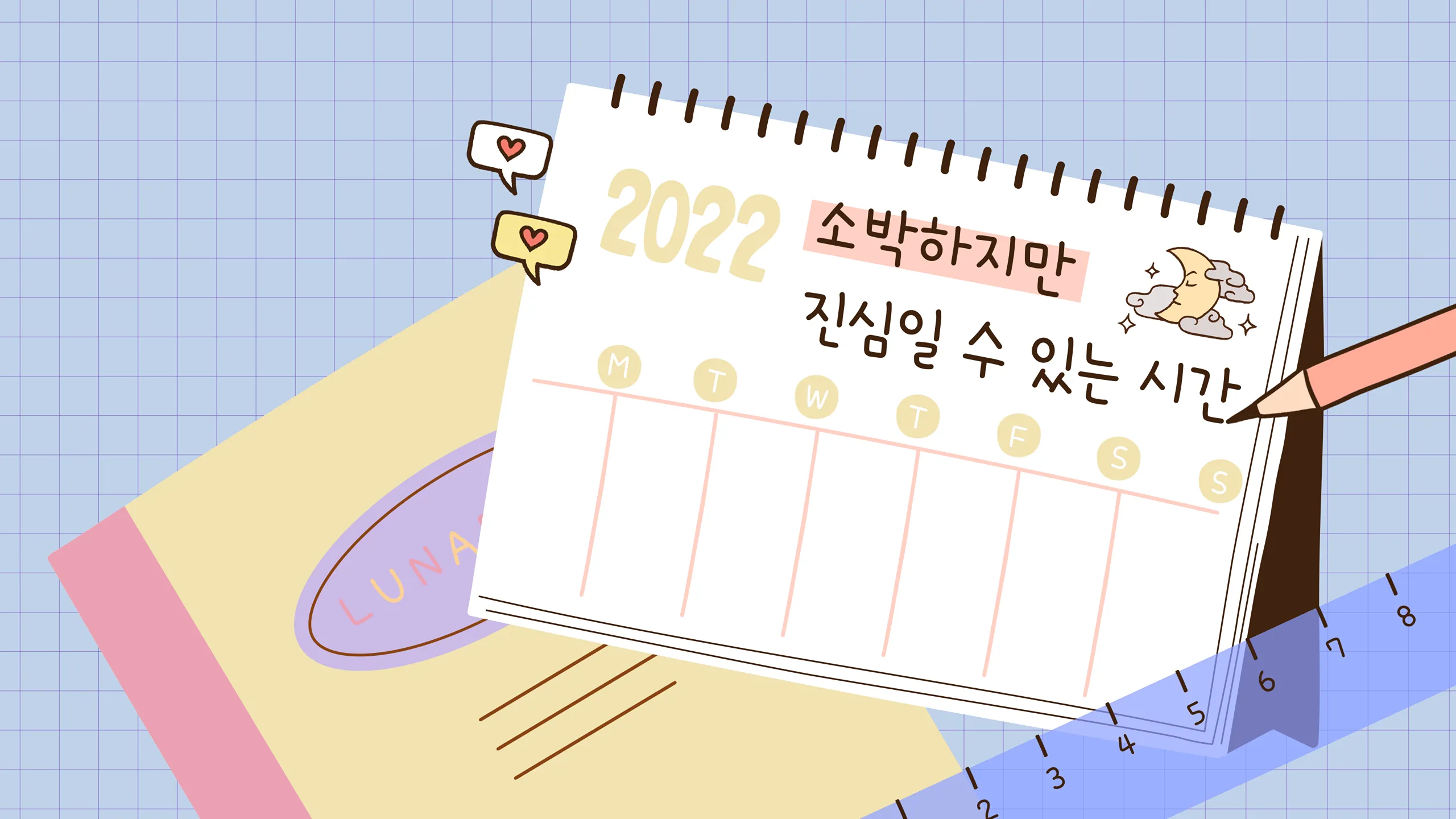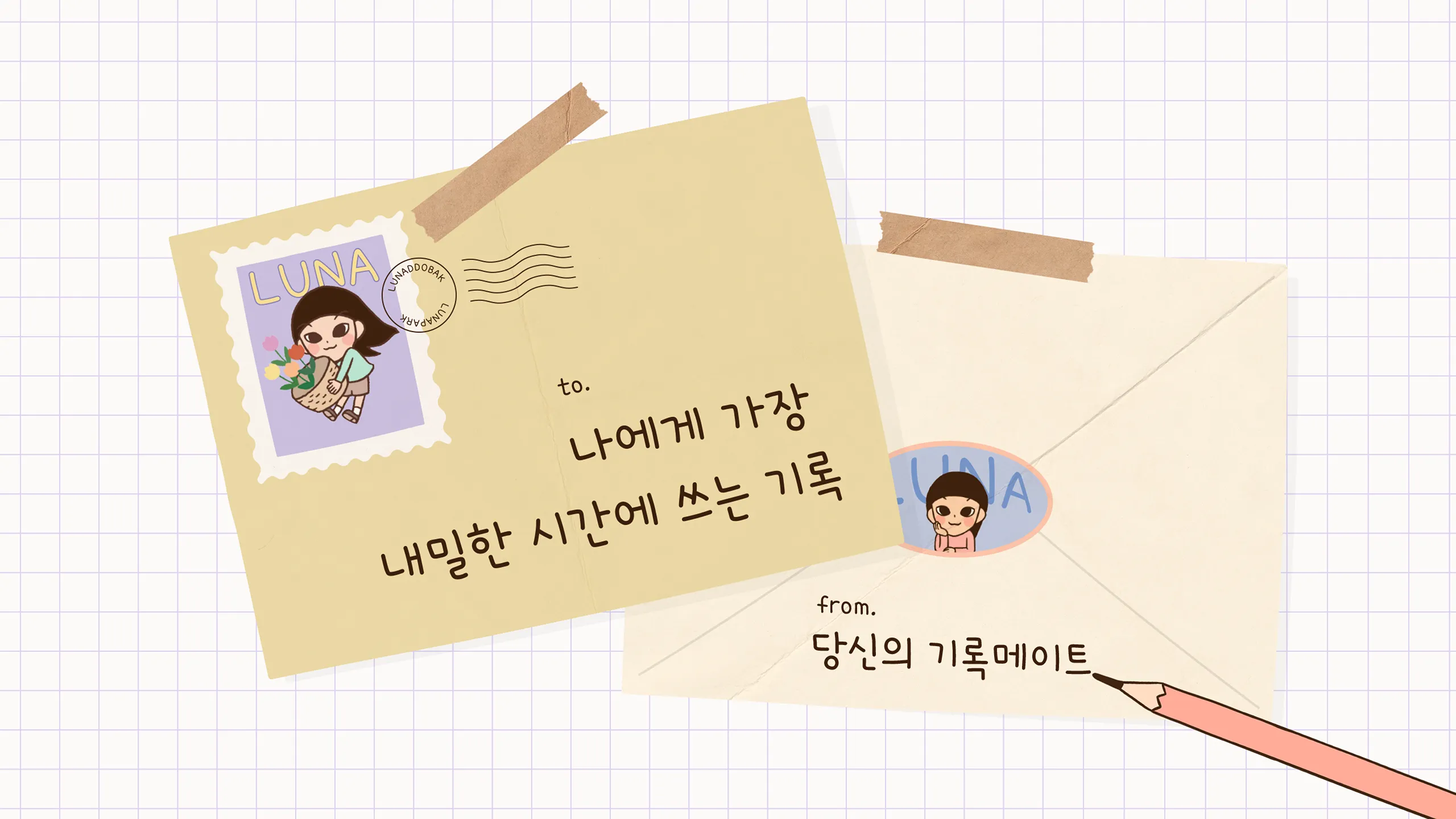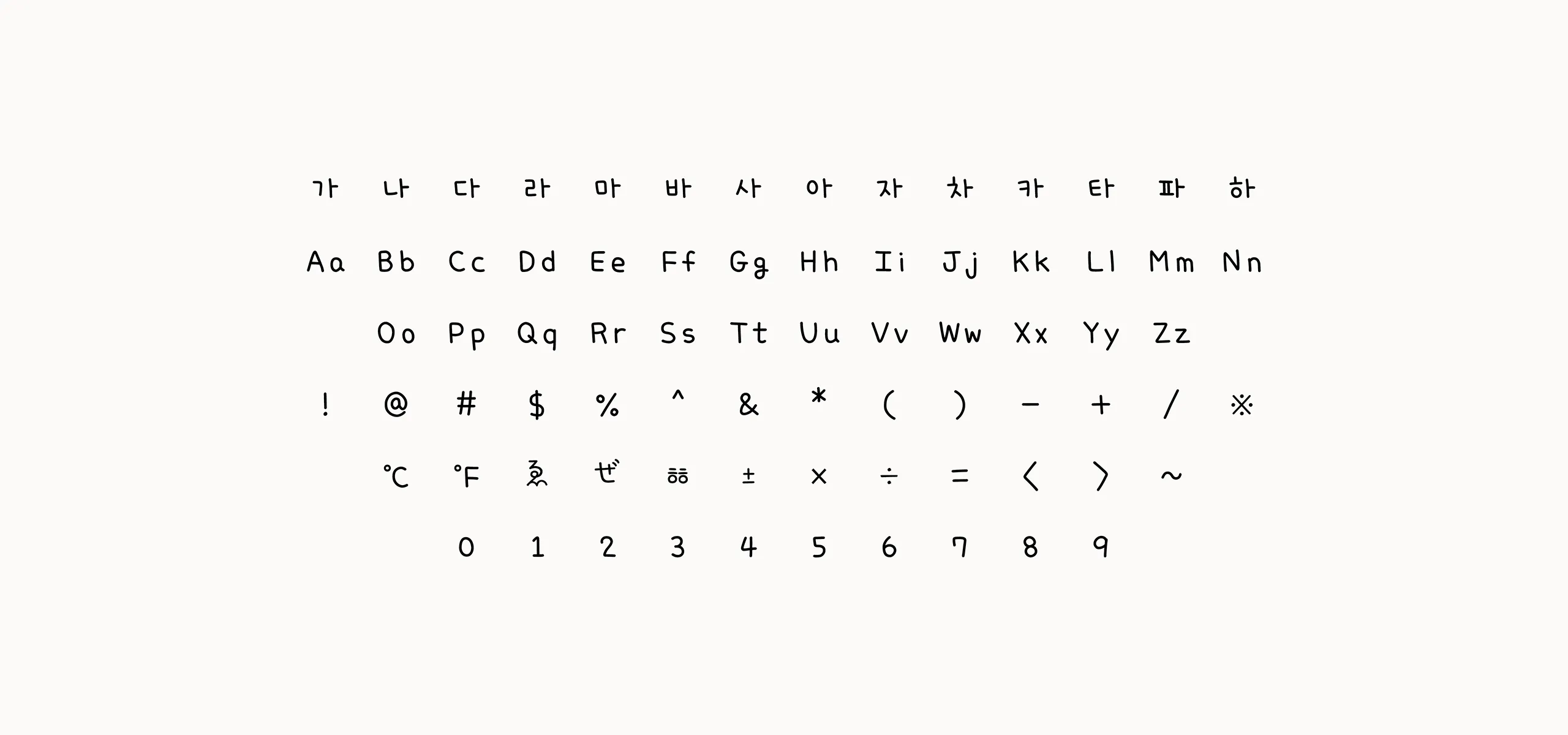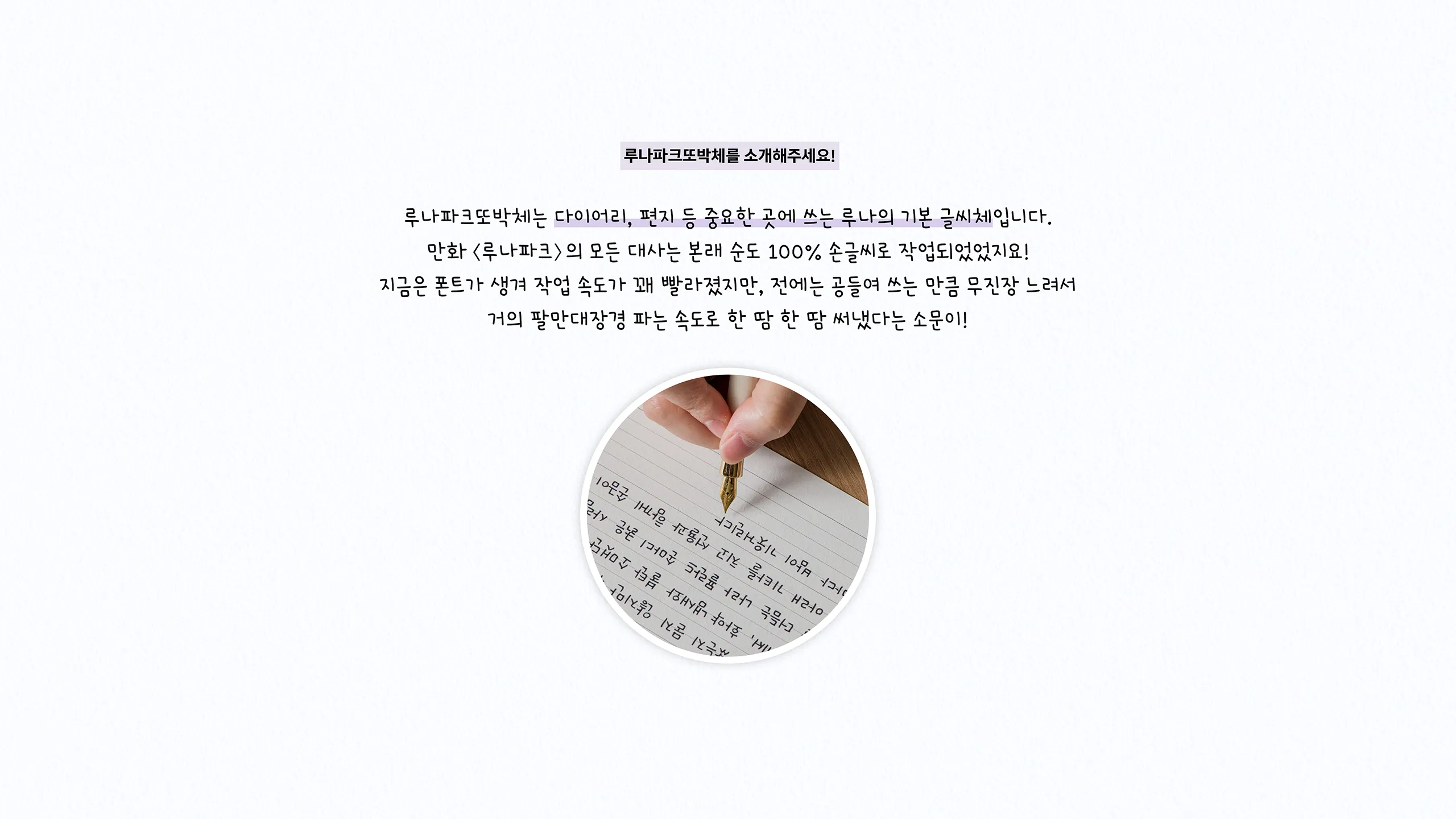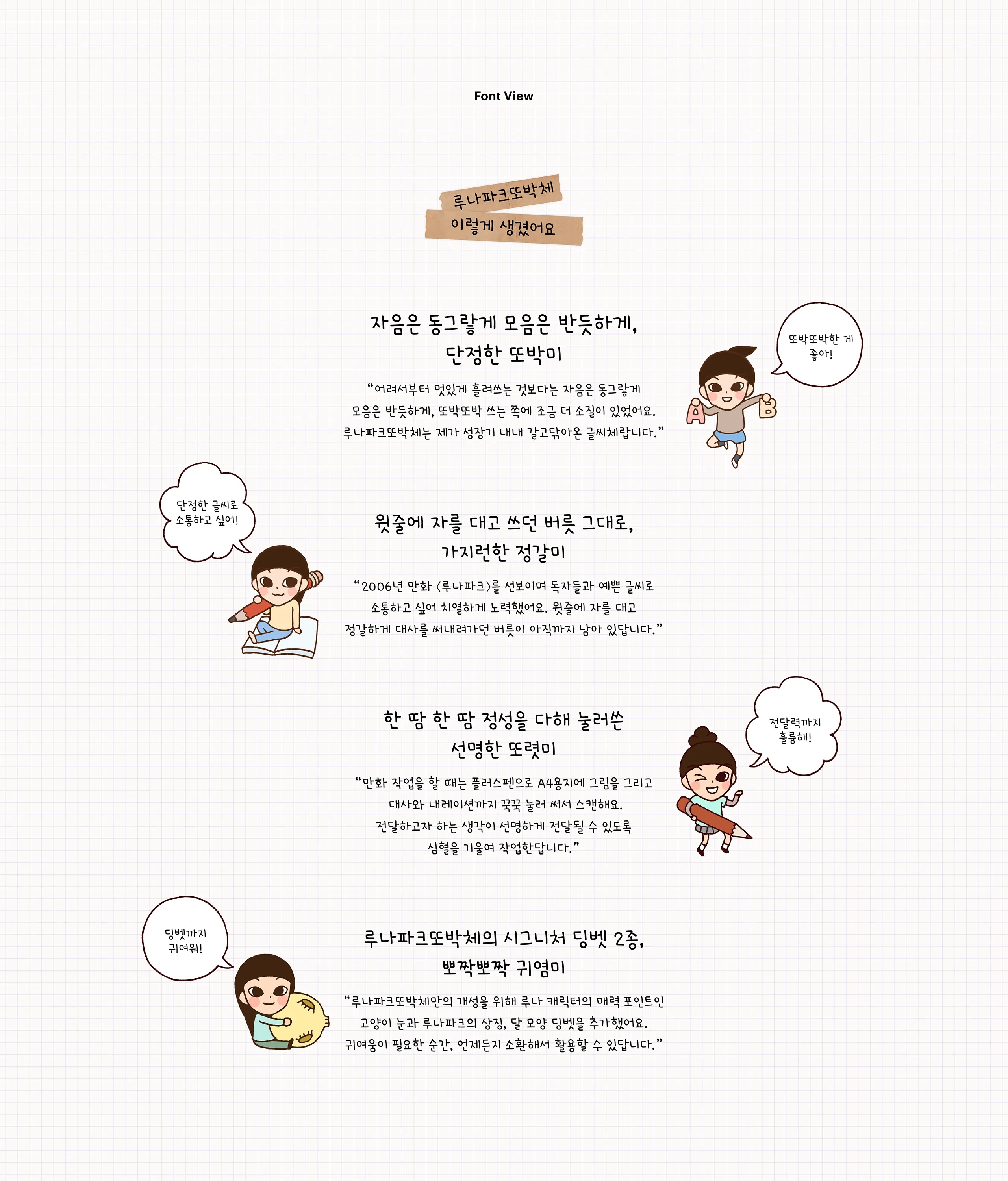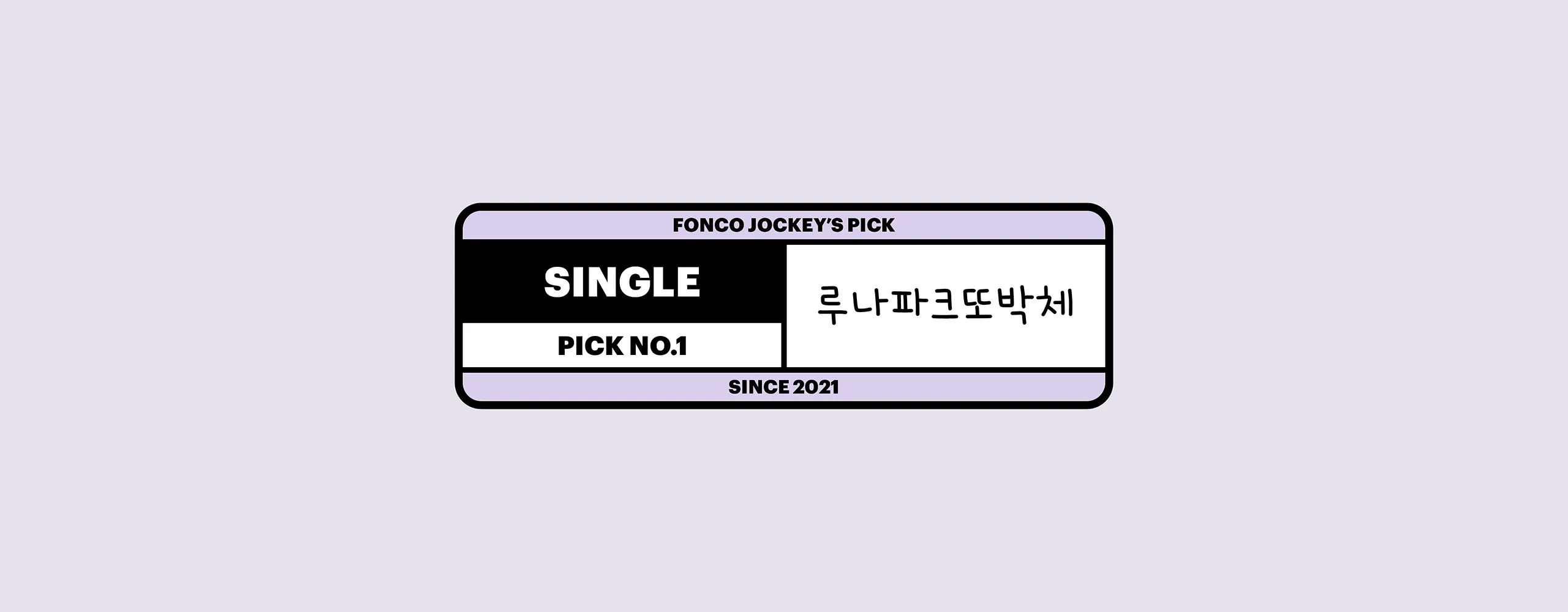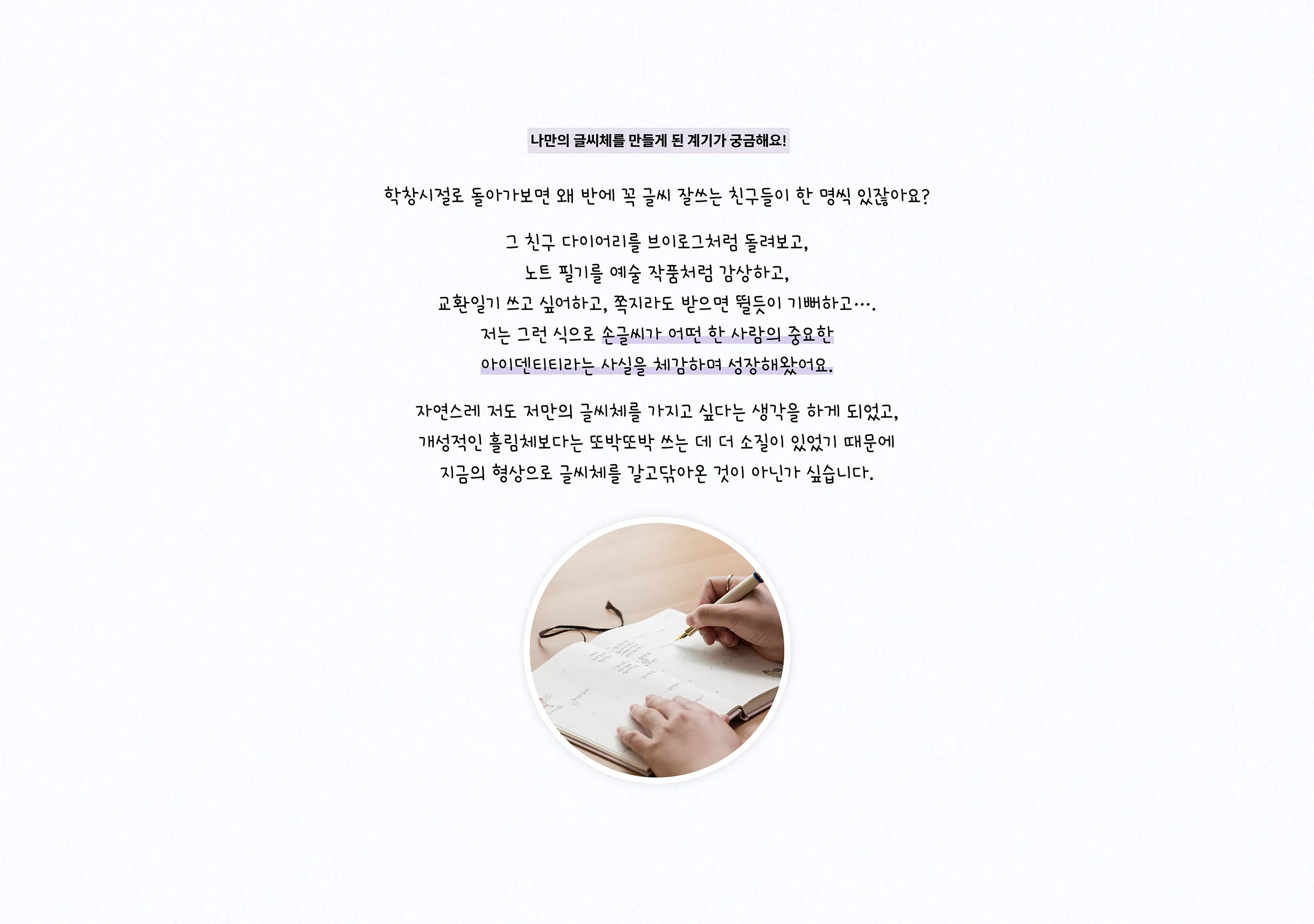
크리에이터 루나(홍인혜)의 무궁무진 창작력의 근간이 되어준 보물 같은 손글씨 폰트
디자이너
루나파크
디자이너 소개
카피라이터, 만화가, 시인을 넘나드는 다재다능한 크리에이터. 그리고 그에 앞서, 기록하지 않으면 애초부터 없던 일이 되어버리는 것 같아서 매일을 또박또박 성실하게 기록해나가는 사람